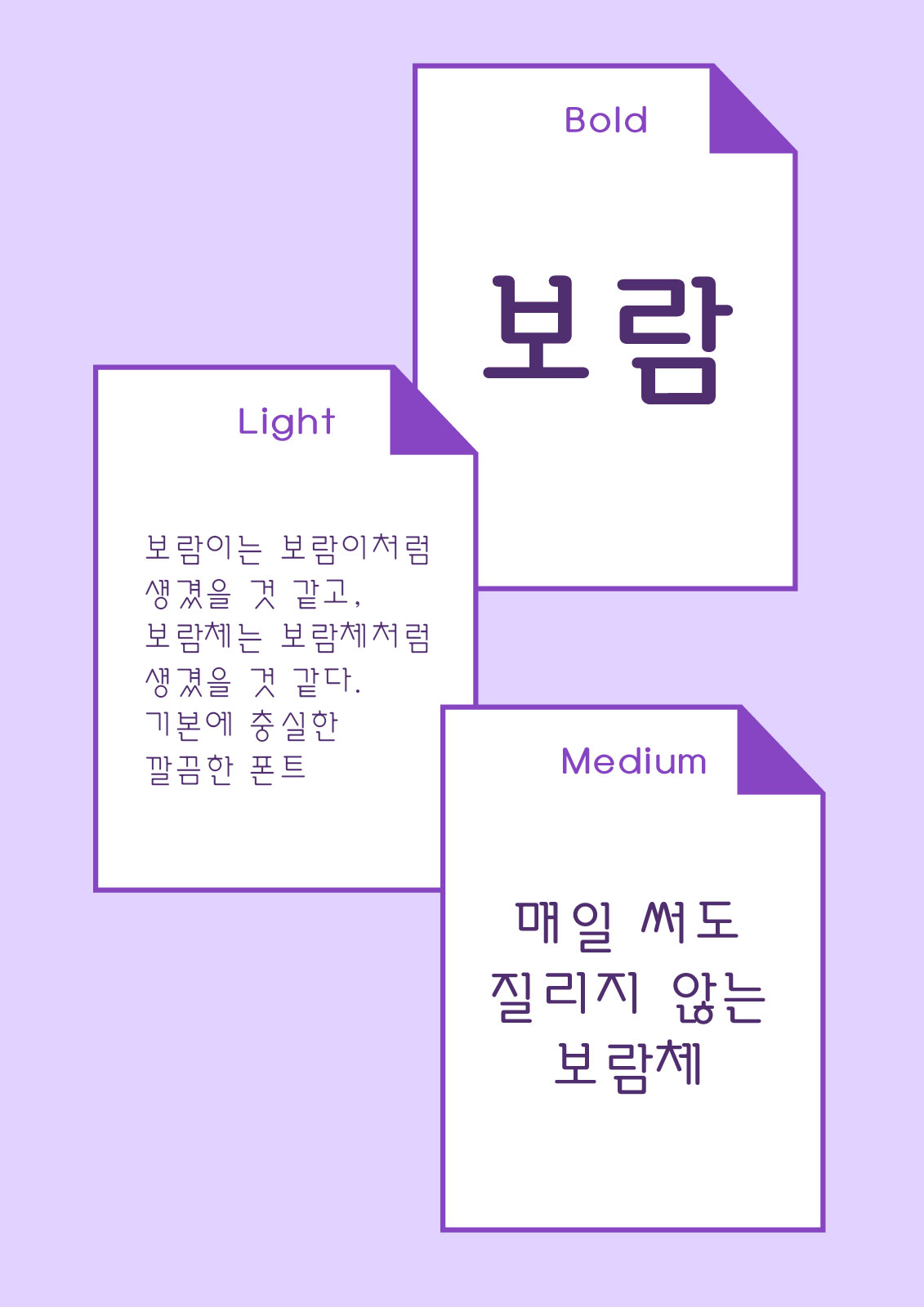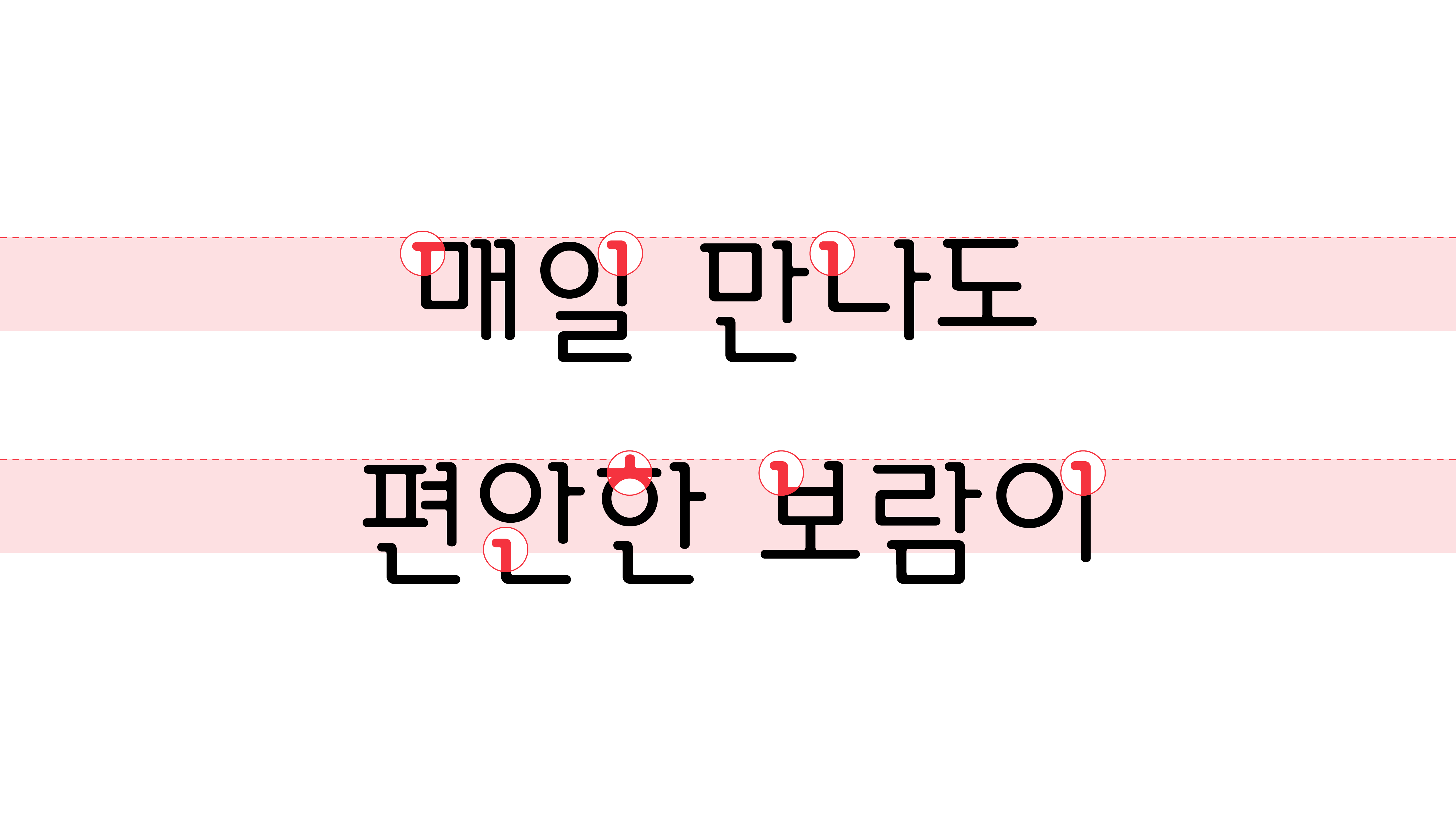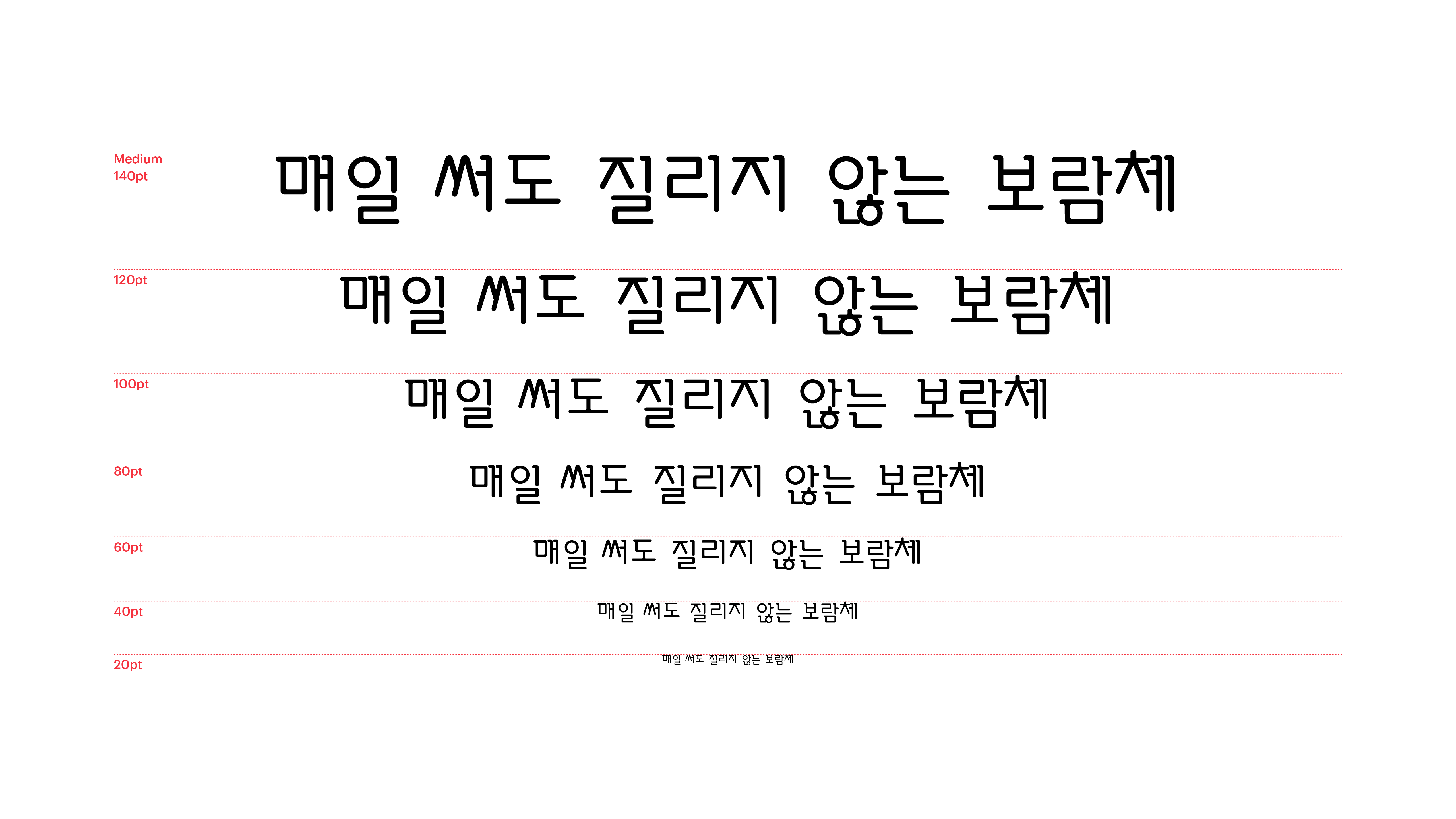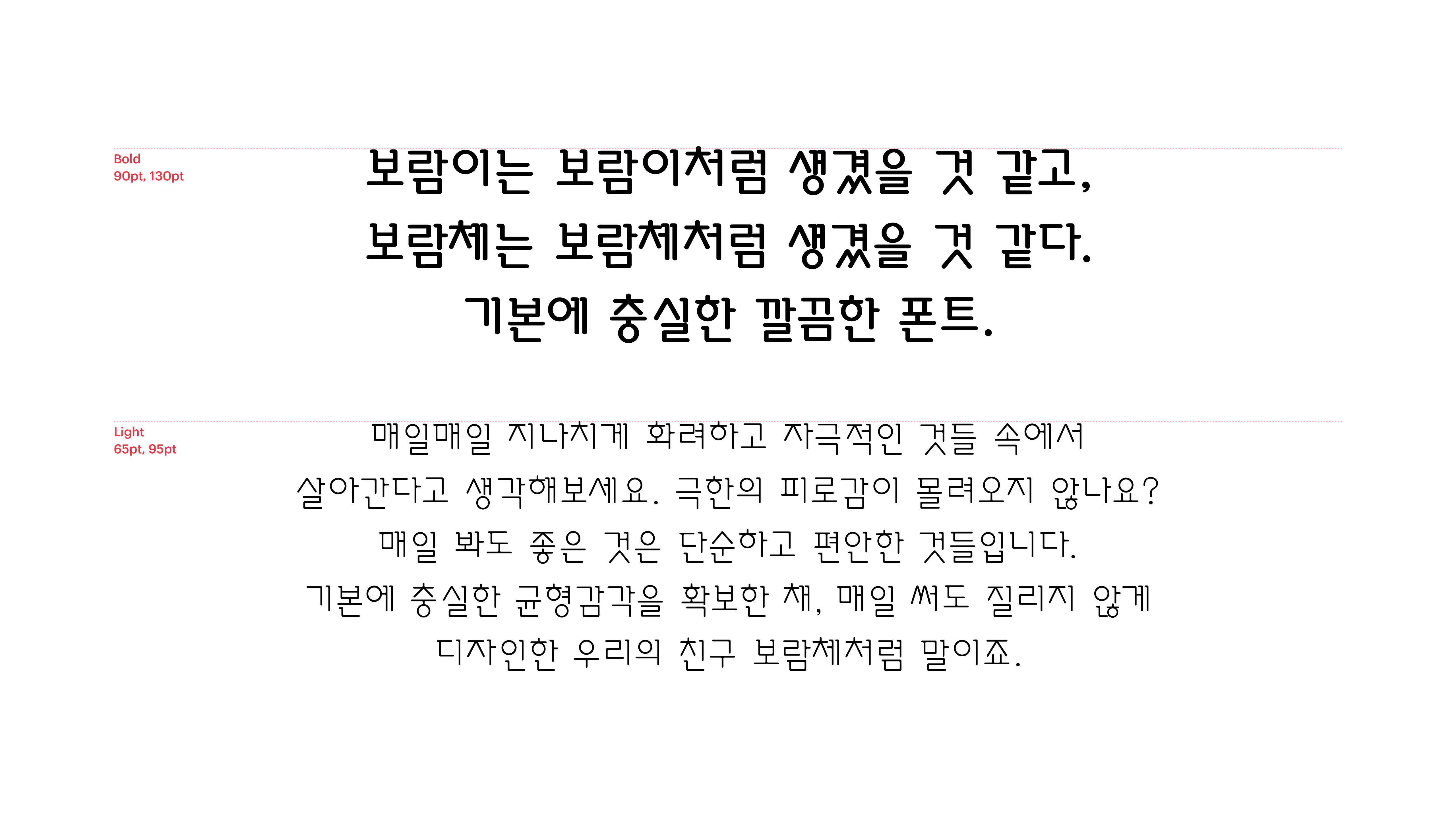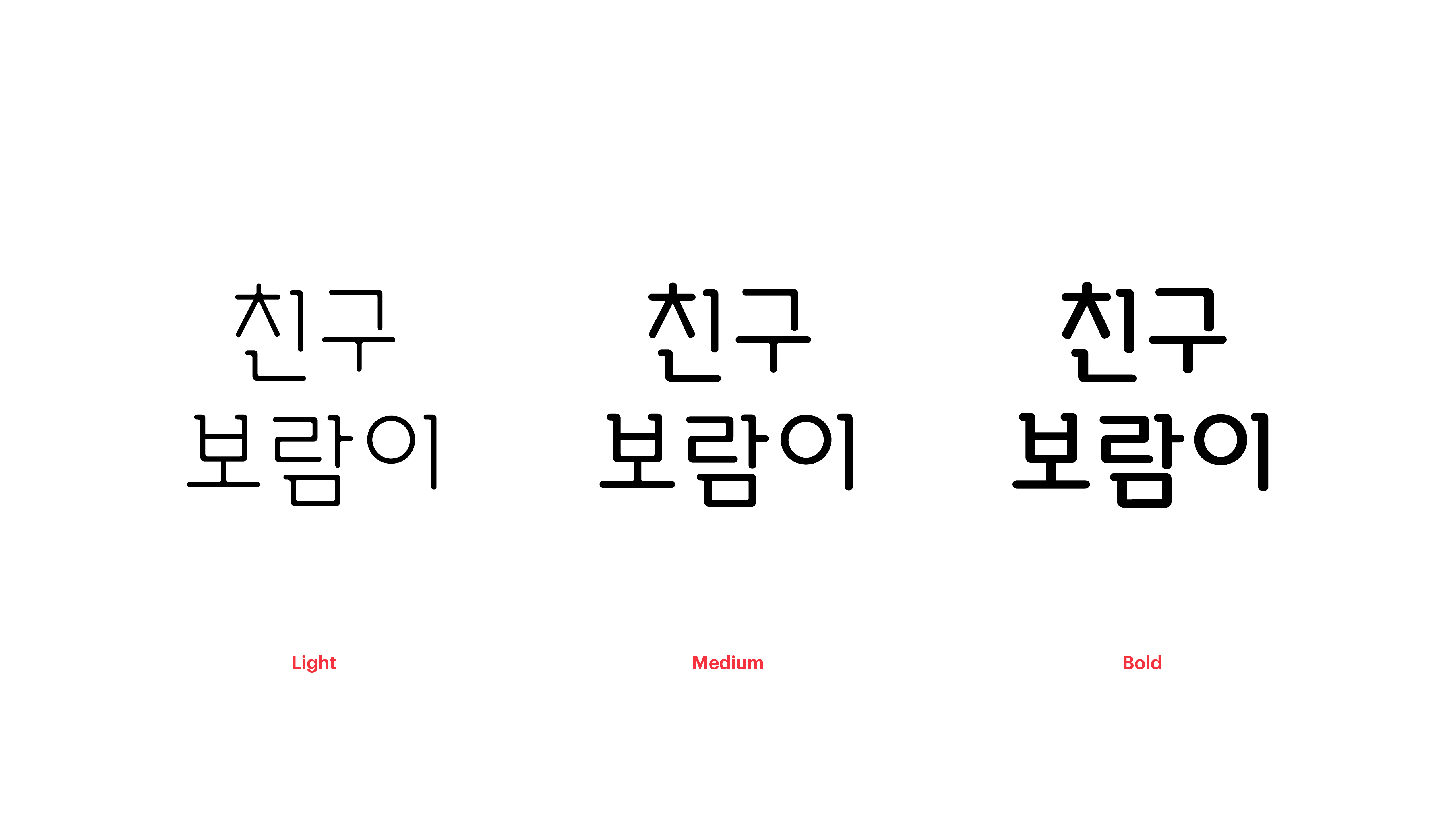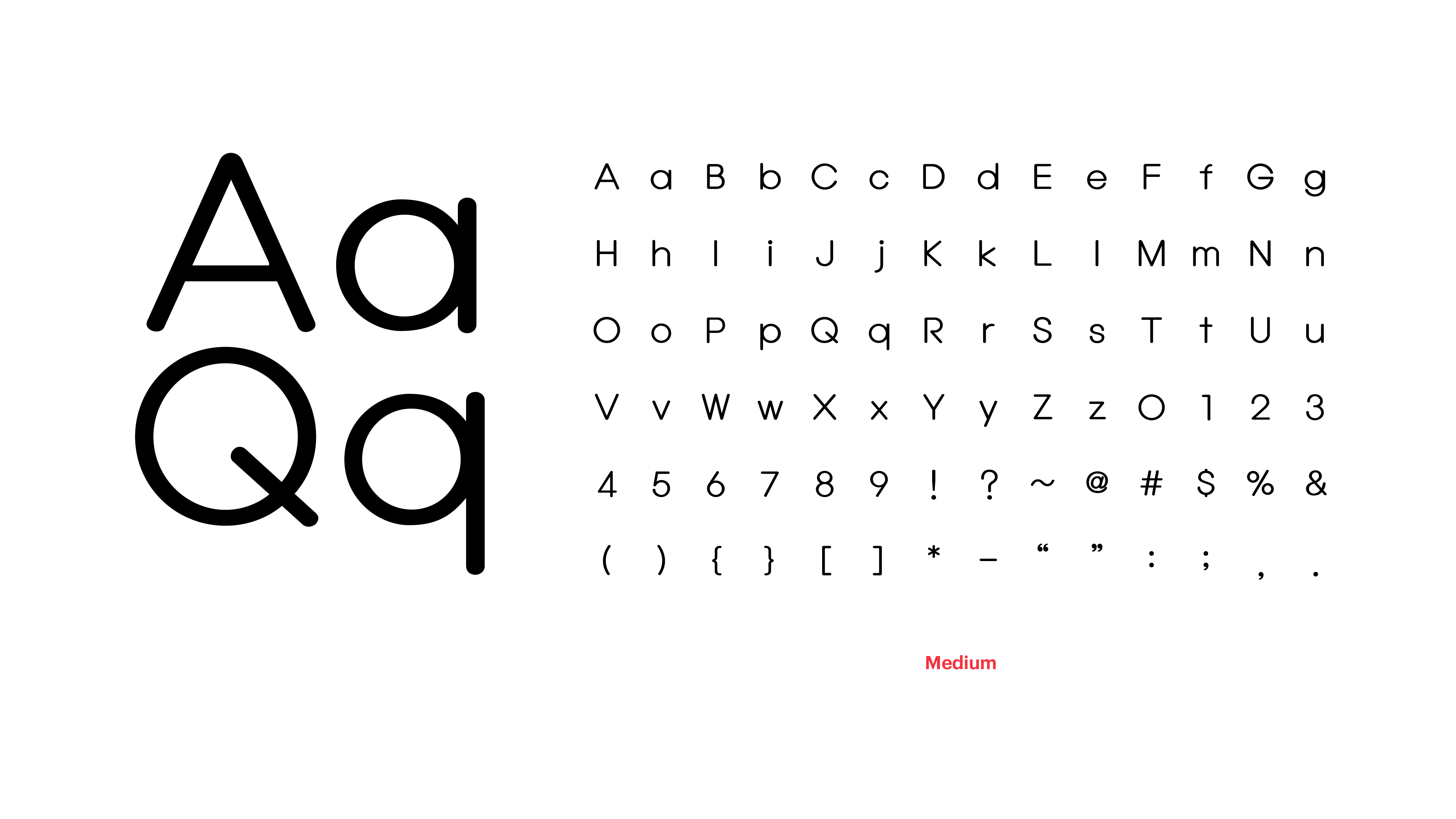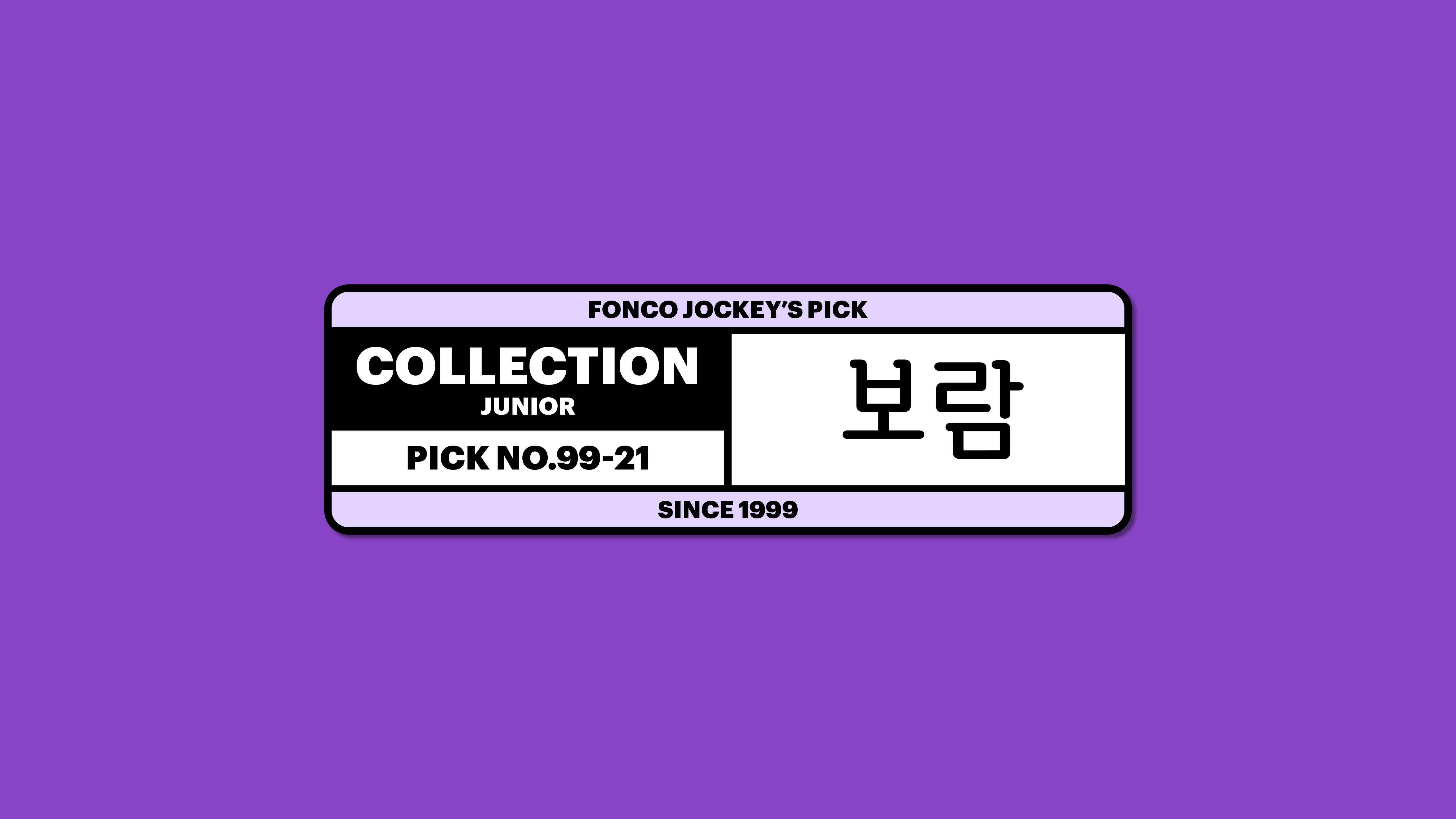
보람
Yoon 보람
매일매일 지나치게 화려하고 자극적인 것들 속에서 살아간다고 생각해보세요. 극한의 피로감이 몰려오지 않나요? 매일 봐도 좋은 것은 단순하고 편안한 것들입니다. 기본에 충실한 균형감각을 확보한 채, 매일 써도 질리지 않게 디자인한 우리의 친구 보람체처럼 말이죠.